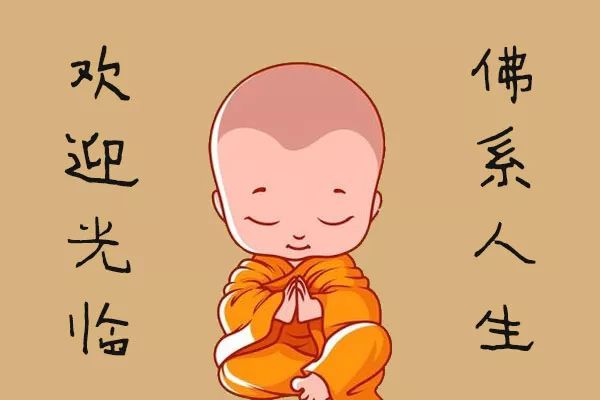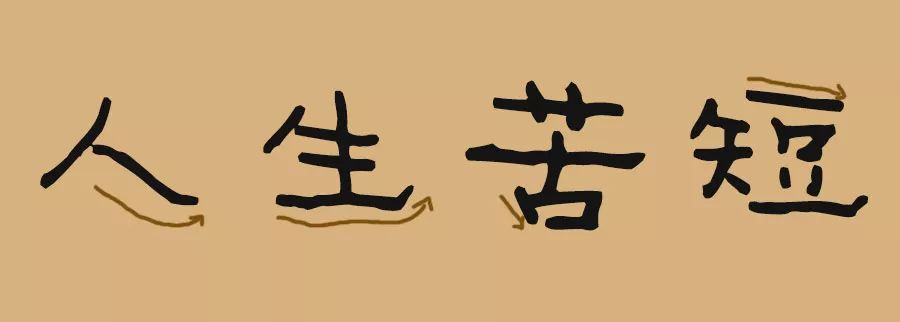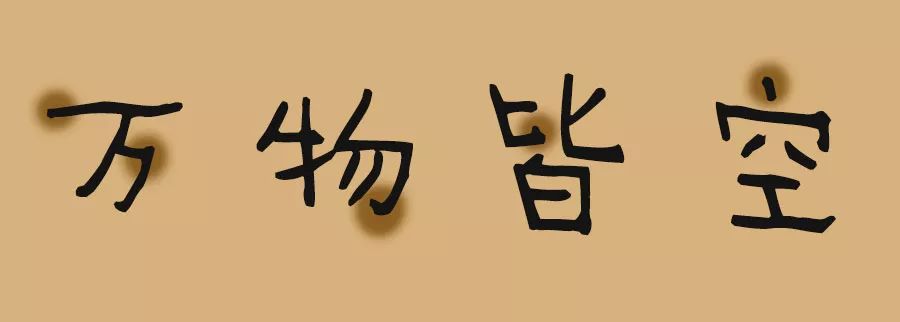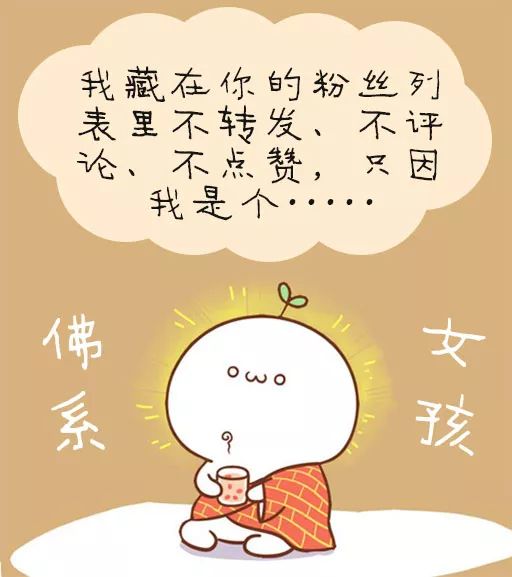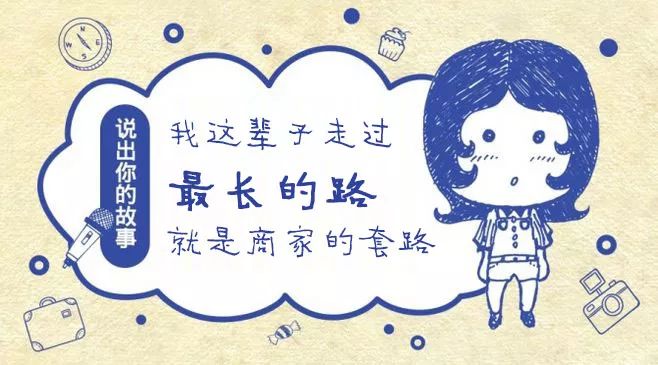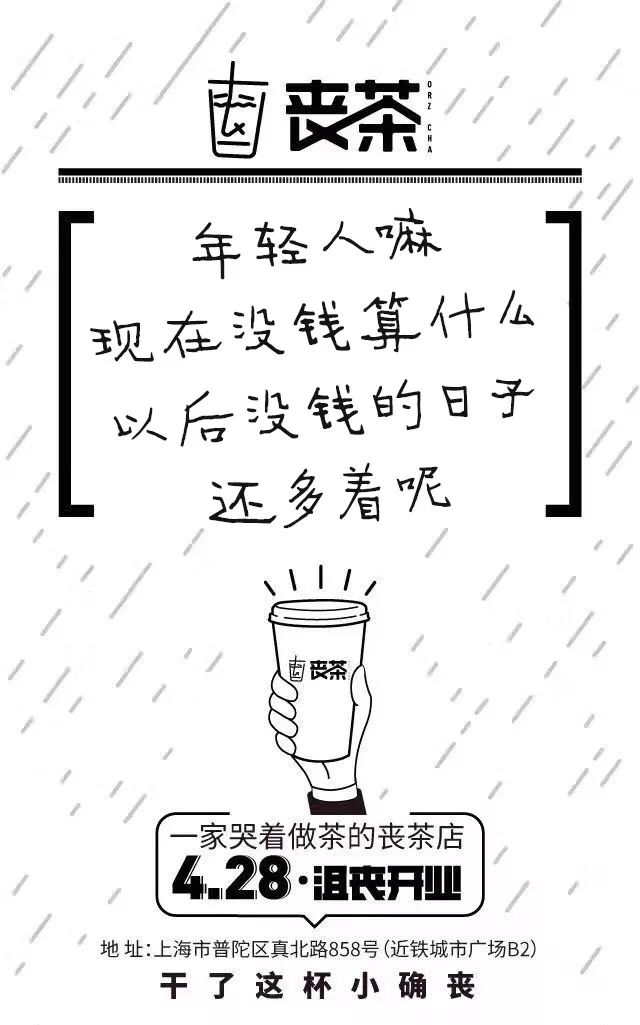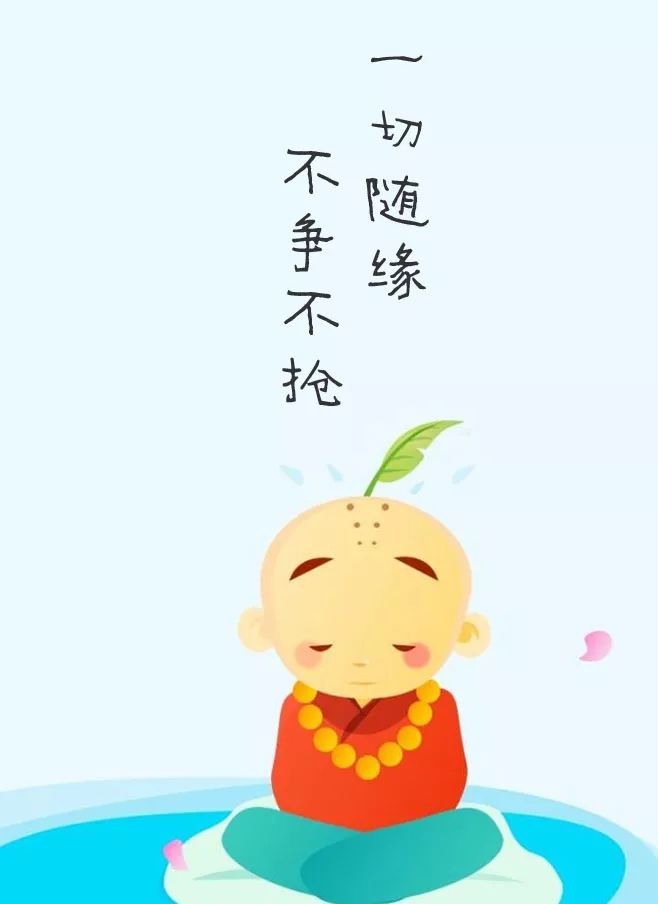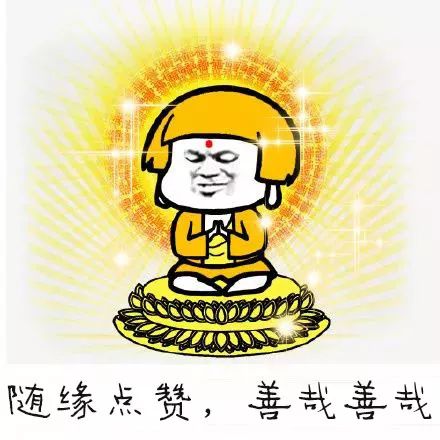
汉仪花农体字体介绍,汉仪花农体使用案例、场景
最近“油腻大叔”还未走远
盆友圈就又被“佛系”点燃
开始以为大家都要皈依佛门
仔细一看才领悟到佛系真谛
怎么都行、看淡一切
简直是要修仙的节奏
而作为佛系设计师
面对甲方爸爸的无限需求难道只能说
错!!!
我们还可以用款佛系字体来书写一些
自己的小情绪
有没有感受到一股风轻云淡之感
左右摇摆懒散的字型结构
搭配看似随意乱画的线条
不禁让人觉得自己离修成正果
只差这一款字的距离
至于字体名字嘛!你记不记都随意
汉仪花农体
文章最后再走一波案例